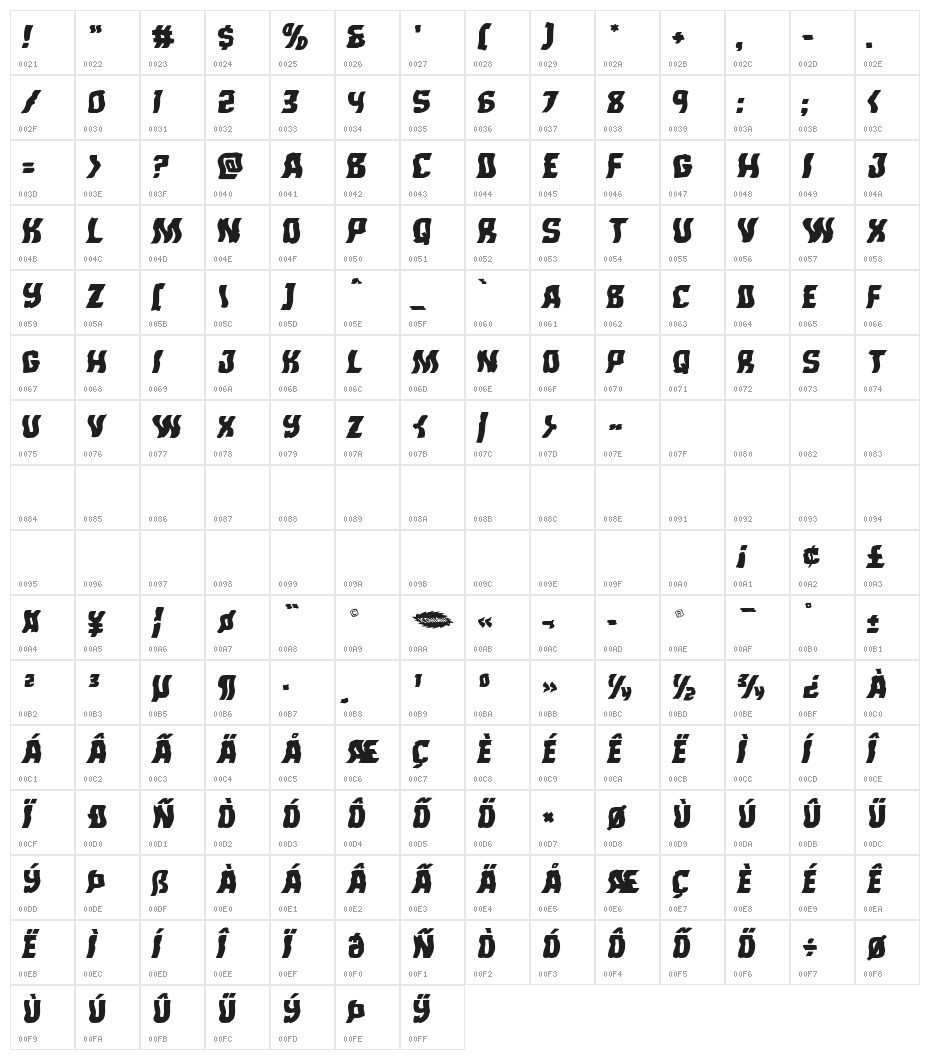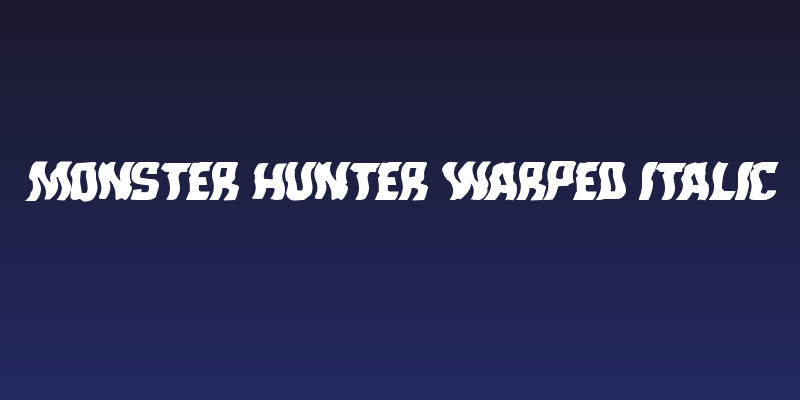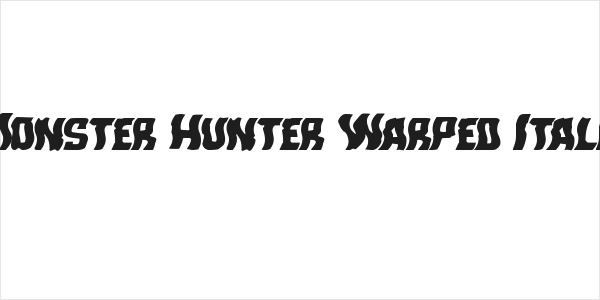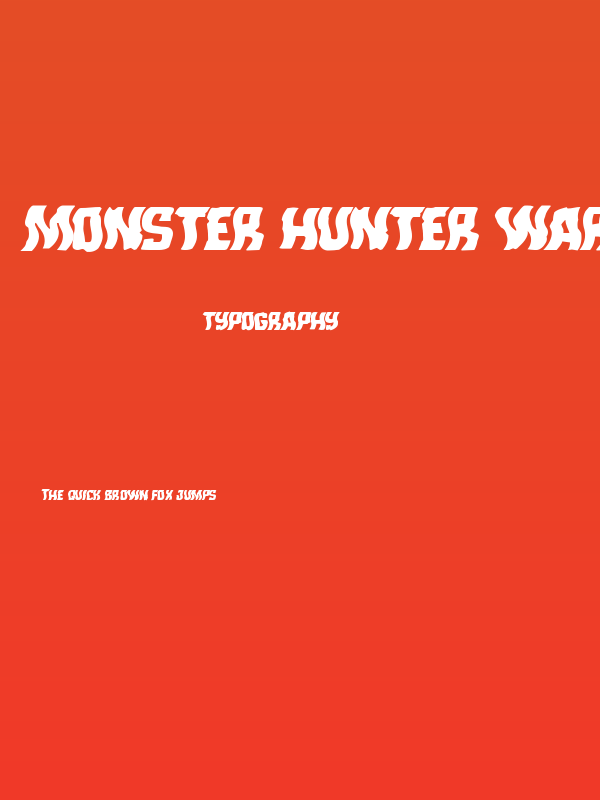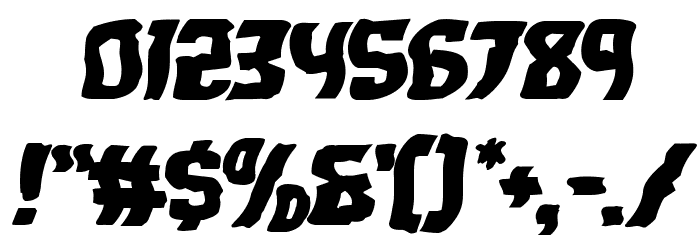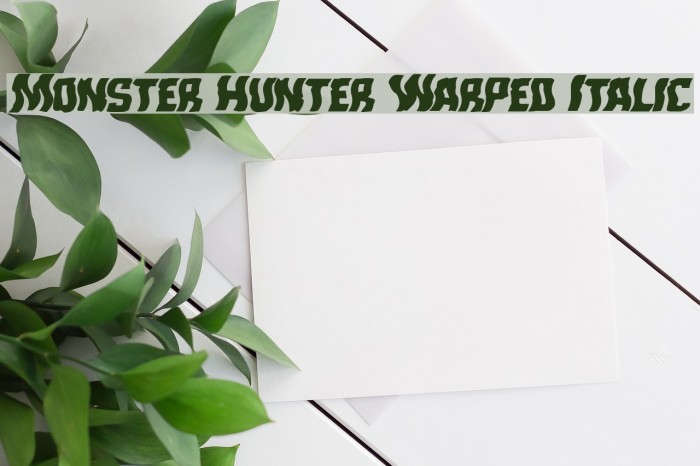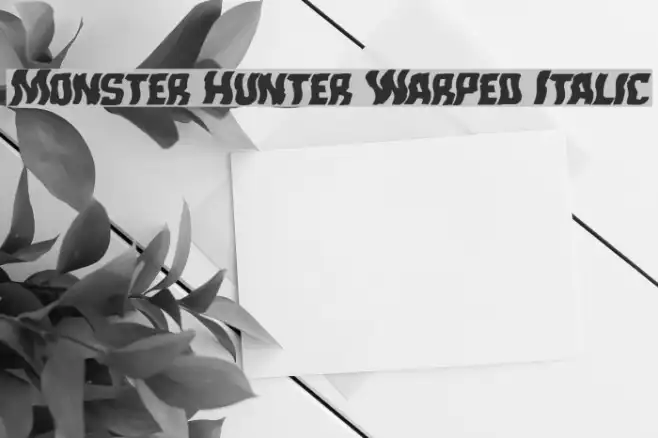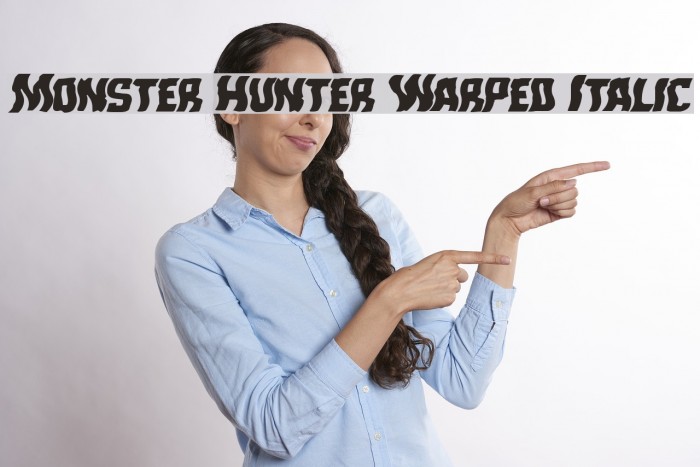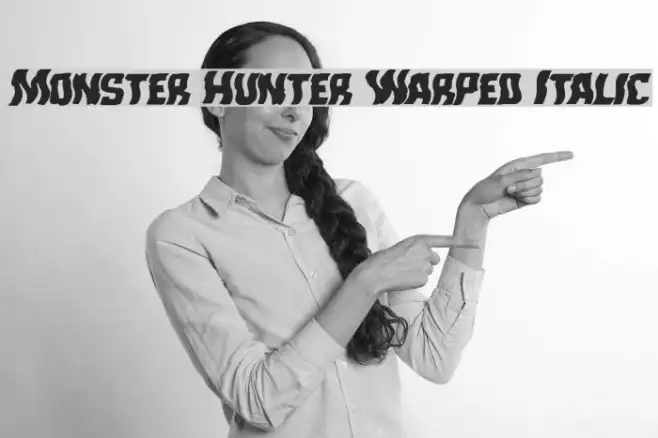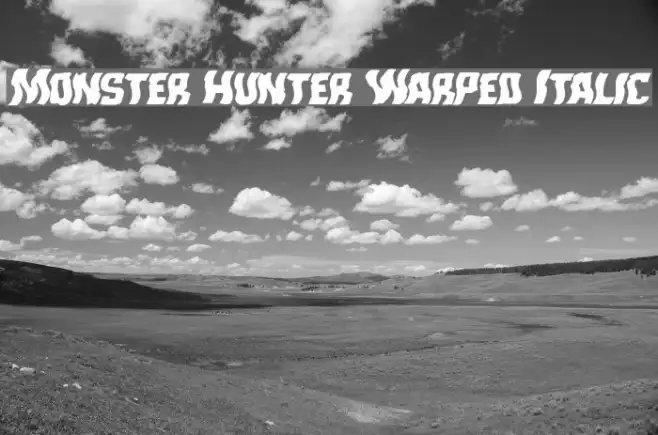
Monster Hunter Warped Italic Font
✎ Thick
| Proyectos propuestos | Ideal for video game titles, movie posters, event flyers, and branding that requires a bold, adventurous look. |